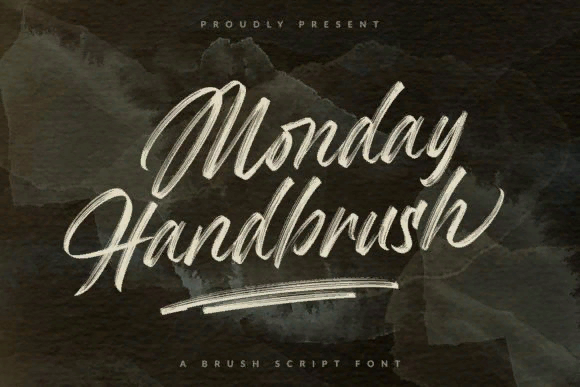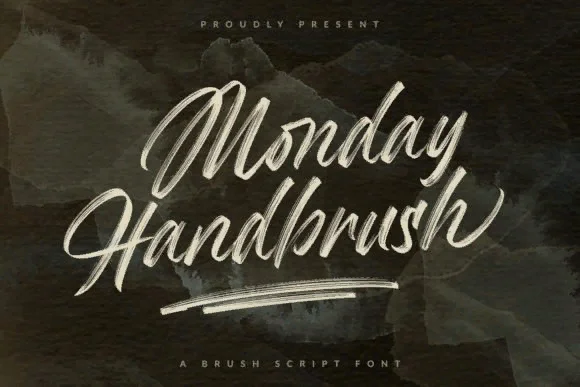
Название: Monday Handbrush Font (2021)
Monday Handbrush - это красивый и матовый рукописный шрифт.
Это лучший выбор для создания привлекательных логотипов, брендинга и цитат.